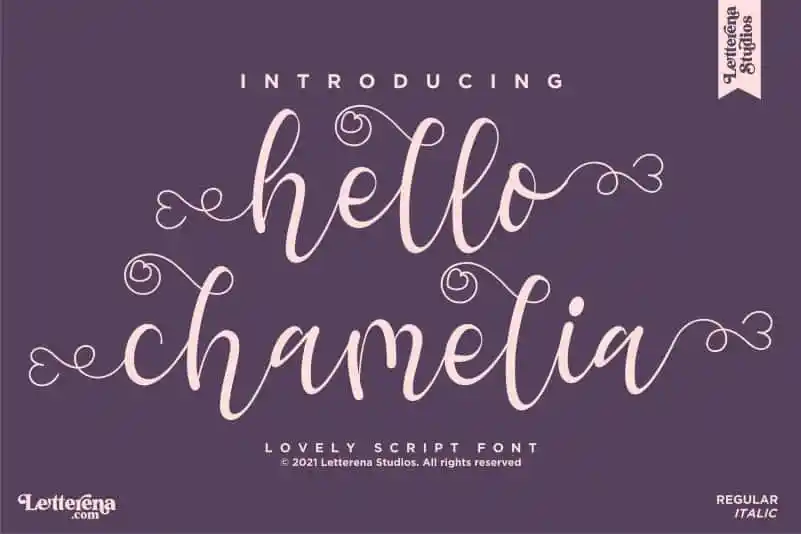
Hello Chamelia Calligraphy Font
A ‘Hello Chamelia Calligraphy Font’, criada pela Letterena Studios, é uma elegante caligrafia que se destaca por sua sofisticação e romantismo. Perfeita para diversos projetos visuais, incluindo logomarcas, embalagens de produtos, capas de livros, etiquetas, cartões de visita, cartões de convidado, adesivos para fotografias e até mesmo selos para eventos especiais. Seja para personalizar sua identidade visual ou tornar seus materiais mais atraentes, este fonte é uma escolha inteligente. E para os amantes do design gráfico, a caligrafia romântica da ‘Hello Chamelia’ irá trazer um toque de encanto e elegância em qualquer projeto que você abordar.